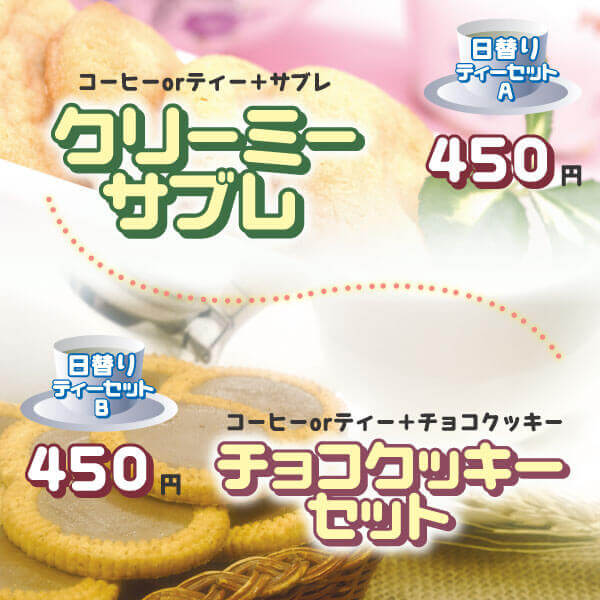
チラシにおすすめのフリーフォント6つ
チラシ作成時におすすめのフリーフォントを6つご紹介します。フォント選びによってチラシの印象も違ってきます。伝えたい商品やサービスのイメージに合ったフォントを選んで効果的なチラシを作りましょう。
BLOCK block
キューブを組み合わせて表現されたフォント。
あいこフォント
20代前後の女性の手書き文字を参考にして作成された無料ダウンロードできる書体。女性誌などと相性が良いのはもちろんのこと、吹き出しなどのコメントにもピッタリです。
たぬき油性マジック
普通紙に油性極太マジックで書いた手書き文字から作成された無料日本語フォント。ひらがな・カタカナ・英数字・記号、JIS第二水準までの漢字及びシフトIBM拡張漢字を収録。
まーと太丸シャドウ
シャドウがかかった太丸な書体。見出しなどに使うと優しい雰囲気を出すことができます。
みんとキッス
80年代を意識した可愛くてポップなフォント。商用利用の場合は製品版の購入が必要です。
渦丸
丸味を帯びたフォント。